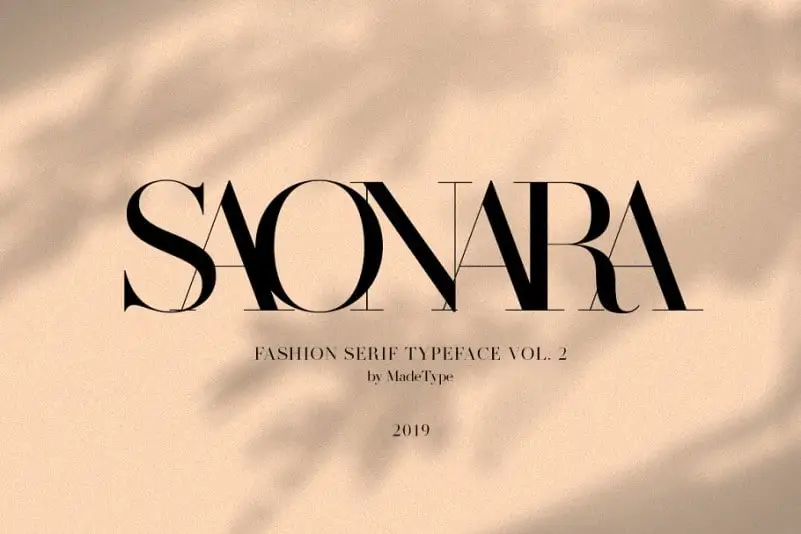
Made Saonara Serif Font – Fonte Grátis
Made Saonara Serif Font – Download Grátis
Made Saonara Serif Font
A Made Saonara Serif é uma tipografia serif com contraste alto e destaca-se por sua elegância e beleza. Inspirada na moda, esta fonte se tornou mais orgânica, mais humana, mais séria, mais confiável e ainda mais luxuosa. Ideal para projetos diversos como moda, revistas, logotipos, marca, fotografia, convites de casamento, citações, cabeçalhos em blogs, cartazes e anúncios. A Made Saonara foi criada pelo designer f0rdesigner, se destacando por ser perfeita para uma ampla gama de usos visuais. Quebre o gelo da sua próxima criação com a Made Saonara, uma fonte que certamente elevará seu design ao próximo nível.